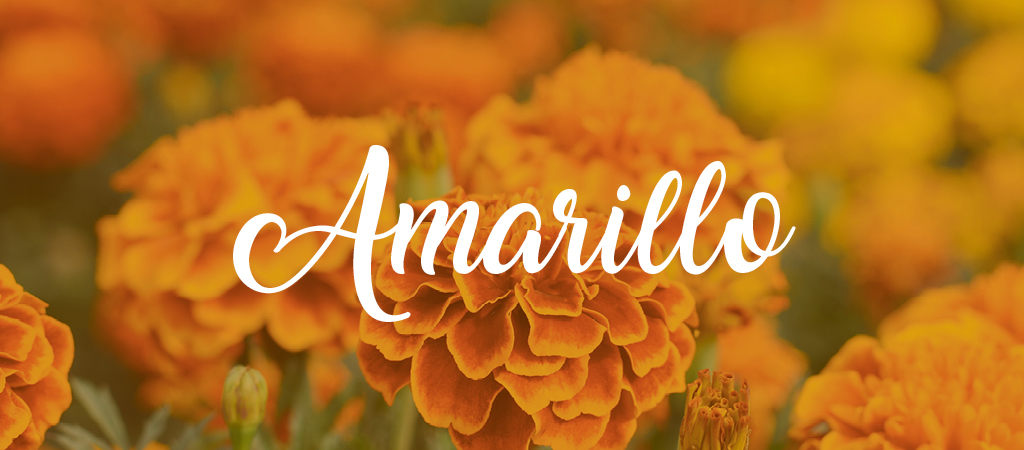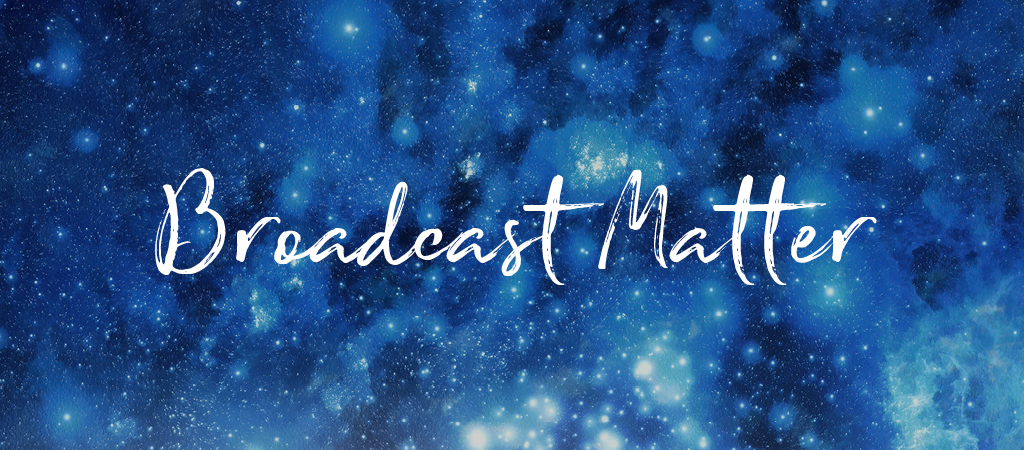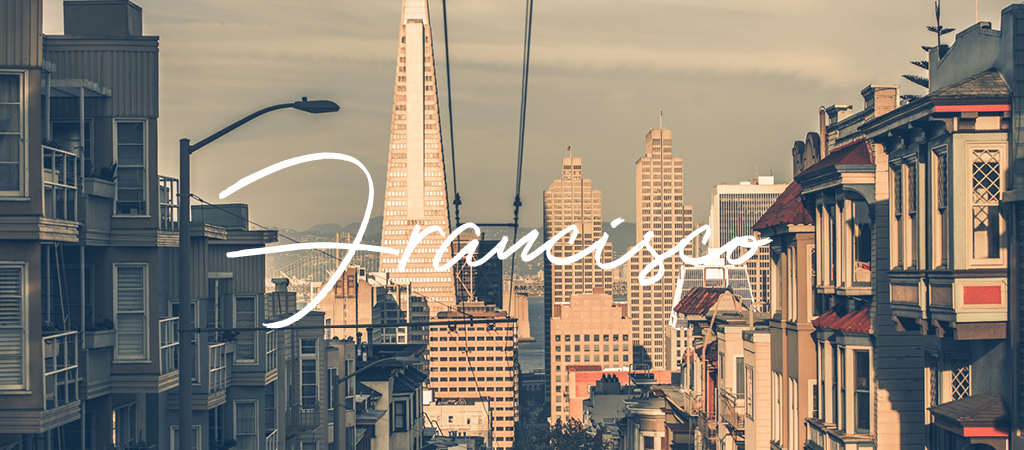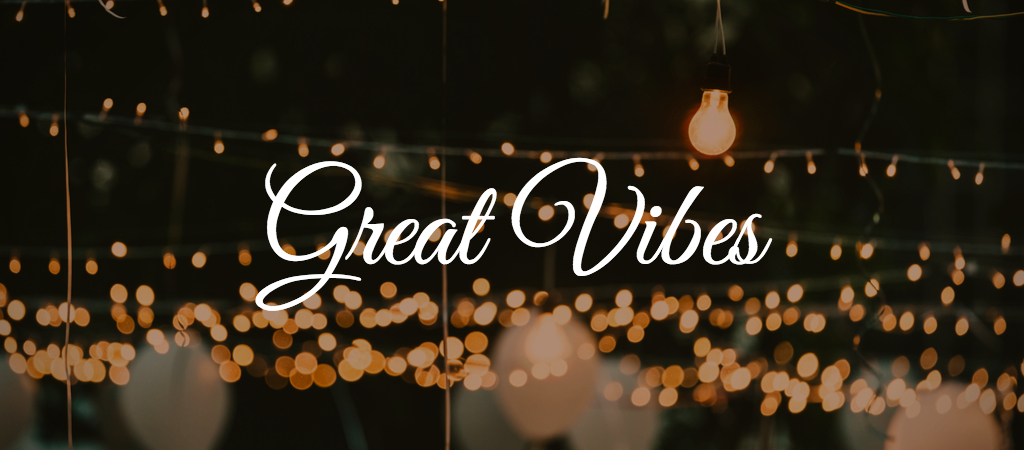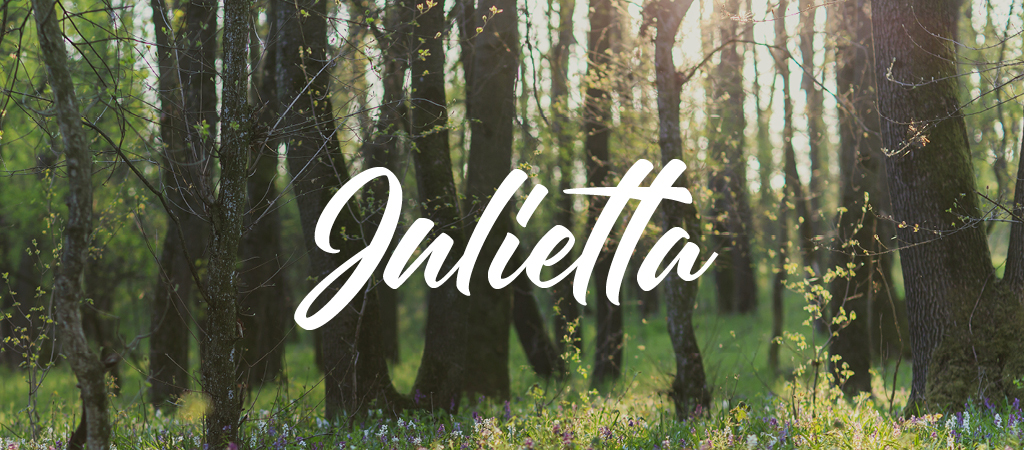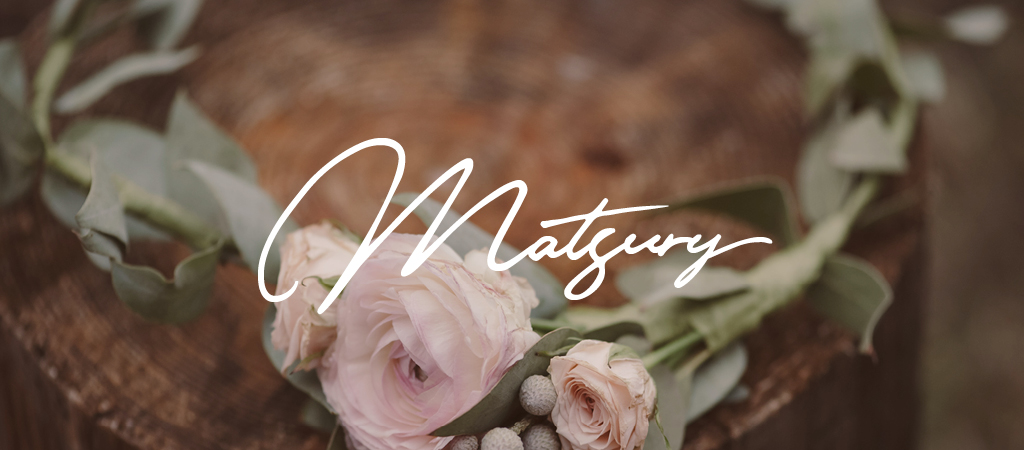
Amarillo là phông chữ đầu tiên trong danh sách của chúng tôi, phông chữ thư pháp được thiết kế bởi Francis Studio. Với tính linh hoạt và các nét đơn giản của nó rất phù hợp cho một tiêu đề thiệp cưới hoặc các văn phòng phẩm: Nếu bạn ghép cặp phông chữ này với phông chữ serif cổ điển chẳng hạn như phông EB Garamond sẽ tạo ra một cái nhìn hoàn hảo.
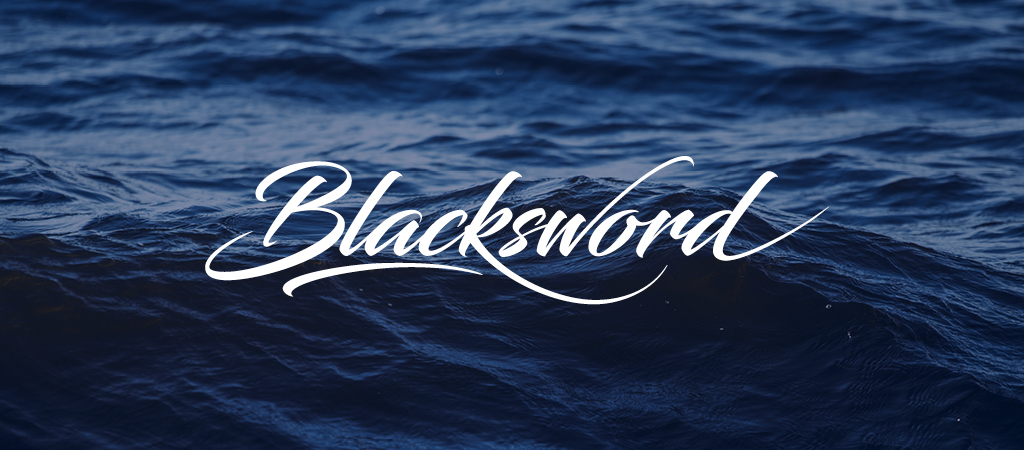
Blacksword, phông chữ được thiết kế bởi Youssef Habchi, là một phông chữ script sắc nét có tính năng swifelike swashes. Kiểu chữ này được sử dụng tốt nhất làm tiêu đề có kích thước lớn, vì các dấu gạch ngang có thể khó đọc ở kích thước nhỏ. Ghép cặp Blacksword với một font sans serif, chẳng hạn như Nunito.
Thêm một liên lạc viết tay vào thiết kế của bạn với phông chữ tập lệnh brush có texture này. Ghép nối Broadcast Matter với một font serif, chẳng hạn như Source Serif Pro.
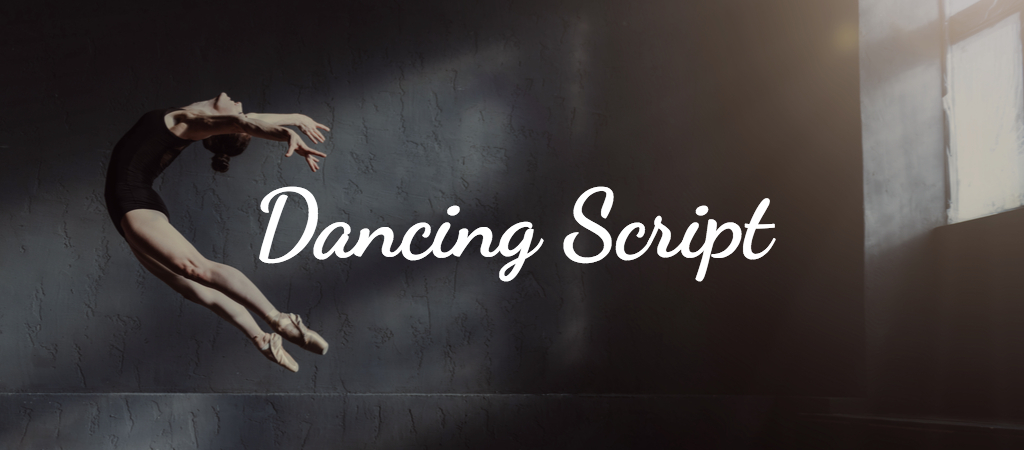
Dancing Script được thiết kế bởi Impallari Type, bắt chước các chuyển động của một vũ công uyển chuyển. Ghép cặp Dancing Script với sans serif, chẳng hạn như Lato, cho một sự tương phản vui tươi.
Phông chữ Francisco do Premier Graphics sản xuất. Đây là một phông chữ có đường nét vẽ tay rất thích hợp để làm chữ ký
Golden Plains, được thiết kế bởi BLKBK Fonts, tạo ra một cảm giác kỳ quái và viết tay với họa tiết tinh tế và dạng chữ hữu cơ.
Great Vibes, một font script trang nhã được thiết kế bởi TypeSETit.
Font chữ này được thiết kế bởi StereoType. Những chữ cái có các đường nét dày nổi bật dựa trên những cảnh quan rừng chi tiết và mơ mộng.
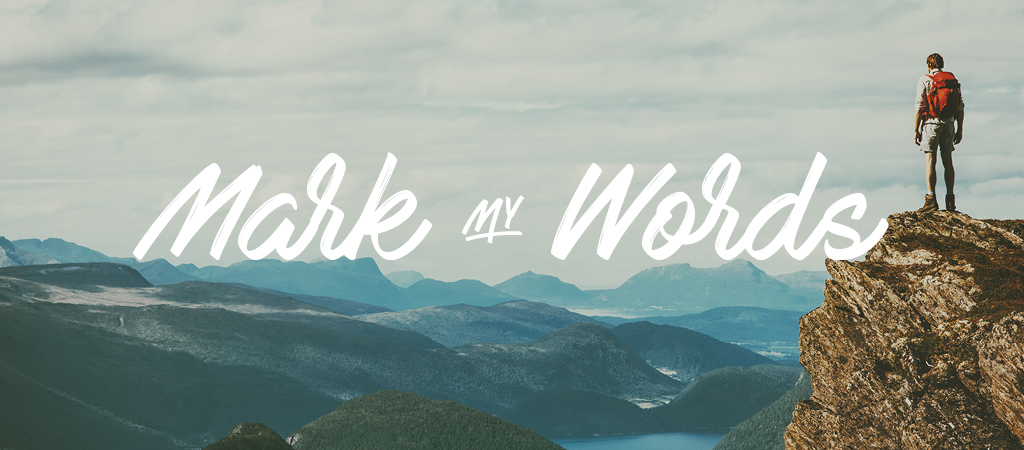
Phông chữ brush này do StereoType sản xuất có các ký tự chữ dày được vẽ bằng một dấu Stabilo. Kết cấu tinh tế giúp Mark My Words có hiệu ứng vẽ tay, hoàn hảo cho việc ghép nối với các nền ảnh chủ đề du lịch, khám phá.
Phong cách kịch bản chữ ký của Matsury thể hiện rất đẹp khi áp dụng cho hình ảnh nền hoa như tạo cảm giác sang trọng.